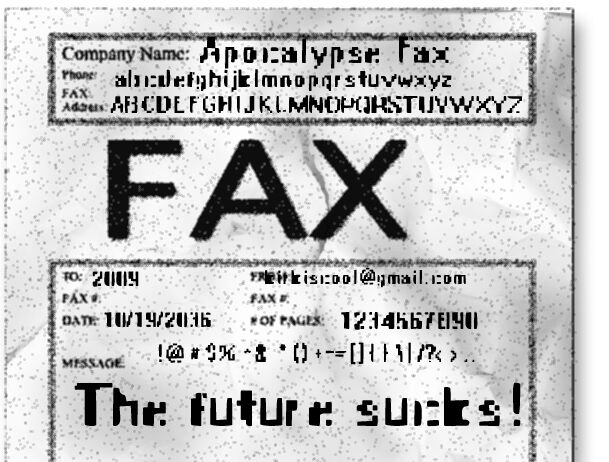
Apocalypse Fax, darmowy pikselowy font bitmapowy autorstwa Kirka Sheltona, przenosi surowy sygnał uszkodzonych ekranów i zniekształconych transmisji. Masywne litery rozpadają się na surowe bloki, a nierówne odstępy i przycięte krawędzie tworzą celowo niestabilny rytm.
Ten darmowy font idealnie pasuje do tytułów gier retro, dystopijnych plakatów, okładek albumów noise, kserowanych zinów i lo-fi plansz tytułowych. Jego poszarpane sylwetki najlepiej sprawdzają się w krótkich nagłówkach lub kompaktowych etykietach, gdzie przypominające faks zniekształcenie staje się głównym motywem wizualnym.